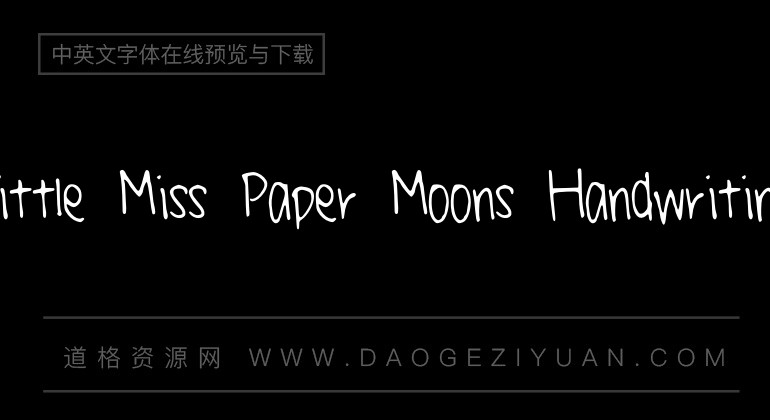
Little Miss Paper Moons Handwriting
Little Miss Paper Moons Handwriting是一款手写字体,它具有流畅、温暖的外观,可以让你的文字看起来更有活力。它使用了清新的曲线,更加具有表现力,而且比较容易让人接受。它的特点是每个字母都有一种自然的曲线,让你的文字看起来更加精致,而且字体间的距离更加合理,让你的文字更易于阅读。
Little Miss Paper Moons Handwriting是一款非常不错的手写艺术字体,具有很好的视觉感,适合于文化类的宣传设计、商业类品牌的广告和产品包装设计以及个性化文字排版等较多场景。